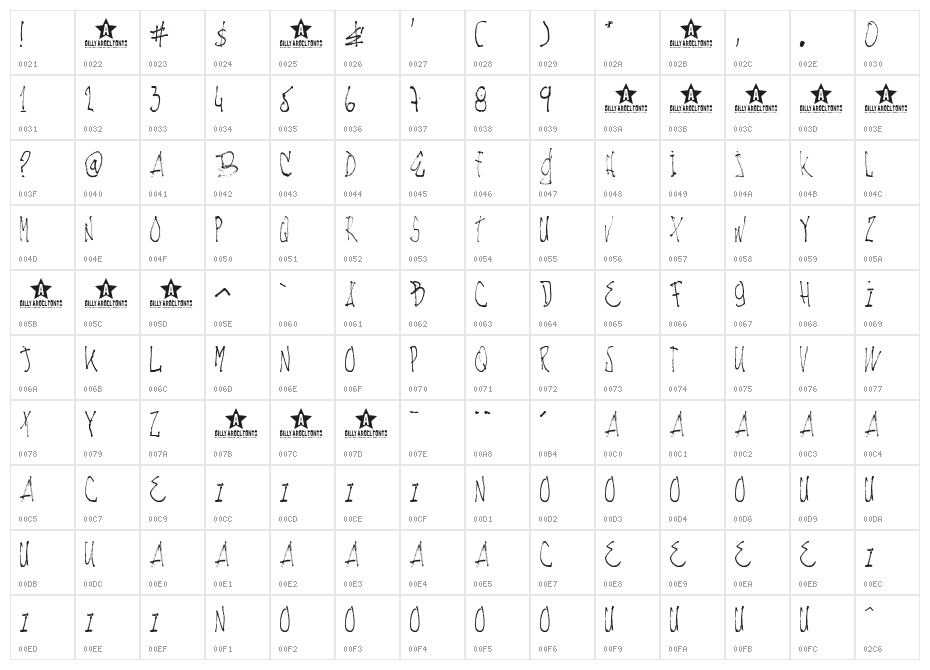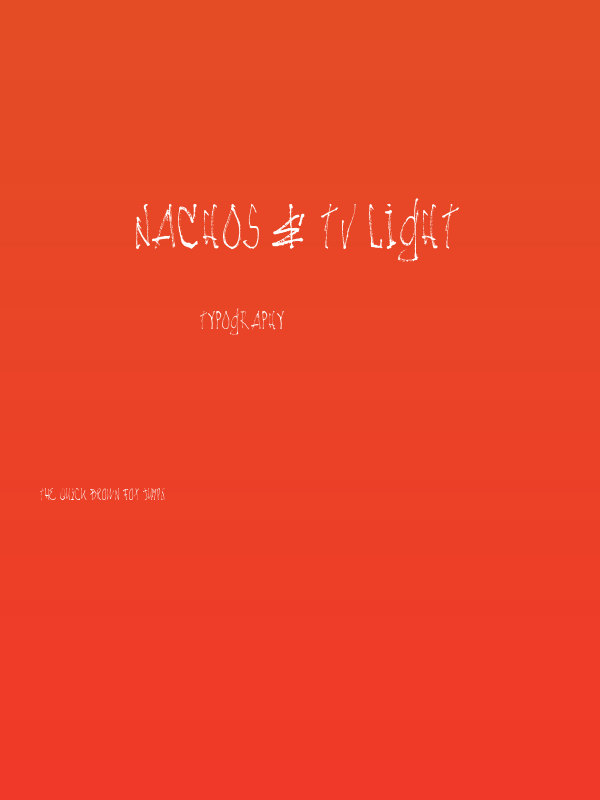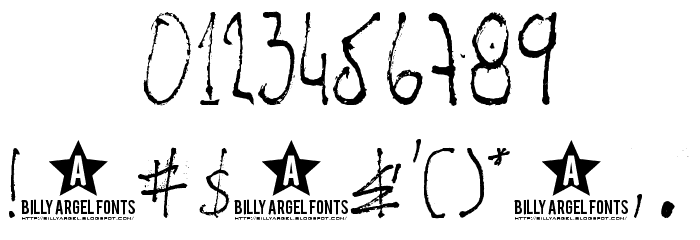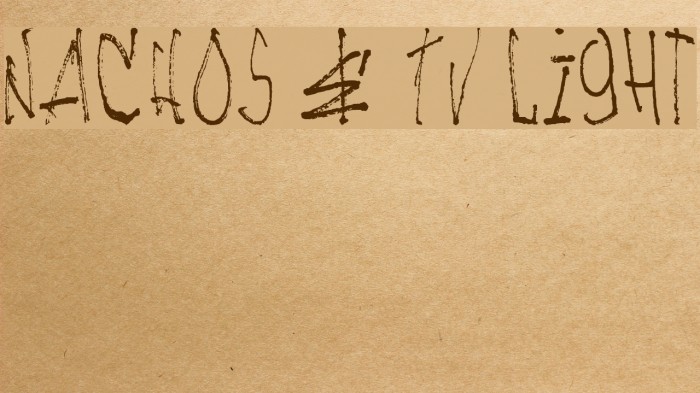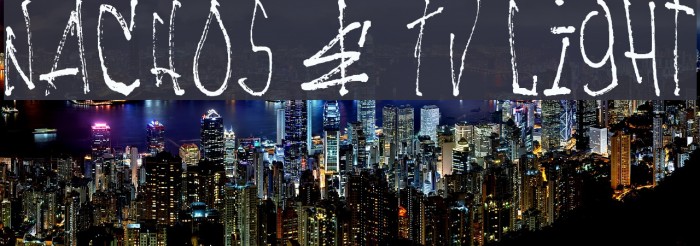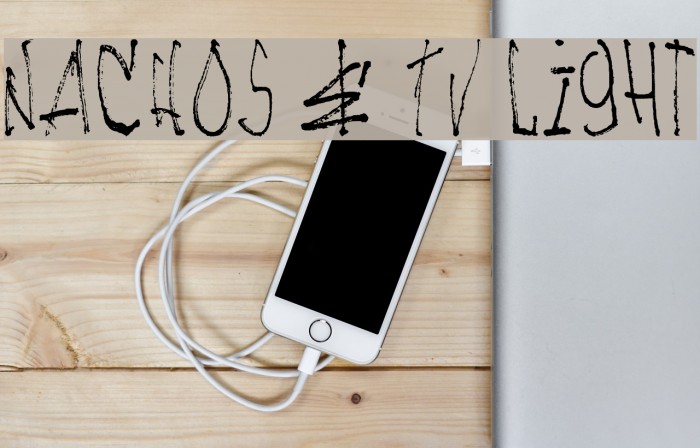
NACHOS & TV Light Font
✎ Cartoon
| 全体的なスタイル | Artistic, Graffiti |
| 用途 | Headlines, Posters, Artistic designs |
| おすすめプロジェクト | Ideal for projects that require a creative and edgy look, such as street art posters, album covers, or urban-themed branding. |